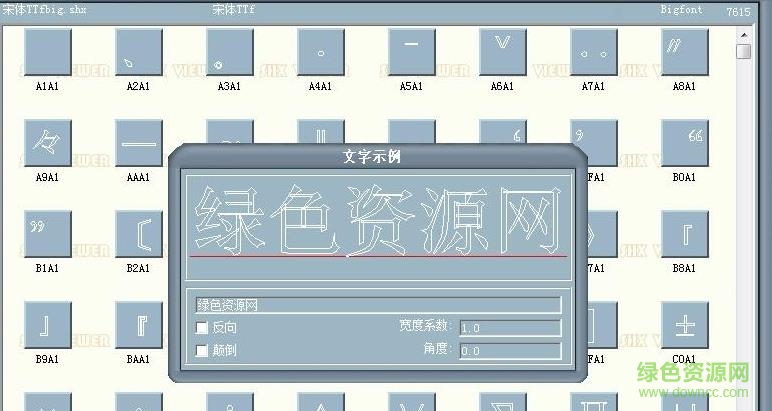
微軟宋體big.shx字體是一款大字體形式的cad字體,讓你能夠在cad軟件中使用大字體效果的宋體文字,從而實(shí)現(xiàn)各項(xiàng)設(shè)計(jì)開(kāi)發(fā),獲得最佳的設(shè)計(jì)圖紙,快來(lái)綠色資源網(wǎng)下載吧!
宋體big.shx通常能夠帶給設(shè)計(jì)師們?cè)谠O(shè)計(jì)過(guò)程中十分優(yōu)質(zhì)的設(shè)計(jì)體驗(yàn),在視覺(jué)效果上擁有十分不錯(cuò)的顯示效果,這款自己將帶給你在設(shè)計(jì)過(guò)程中最佳的設(shè)計(jì)效果!
老宋體及其藝術(shù)風(fēng)格
老宋體,橫較細(xì),豎較粗,體較方,橫畫(huà)右側(cè)扛肩較大,是應(yīng)用最廣、歷史最久的美術(shù)印刷字體。
其藝術(shù)風(fēng)格:端莊、典雅、清正、秀麗。